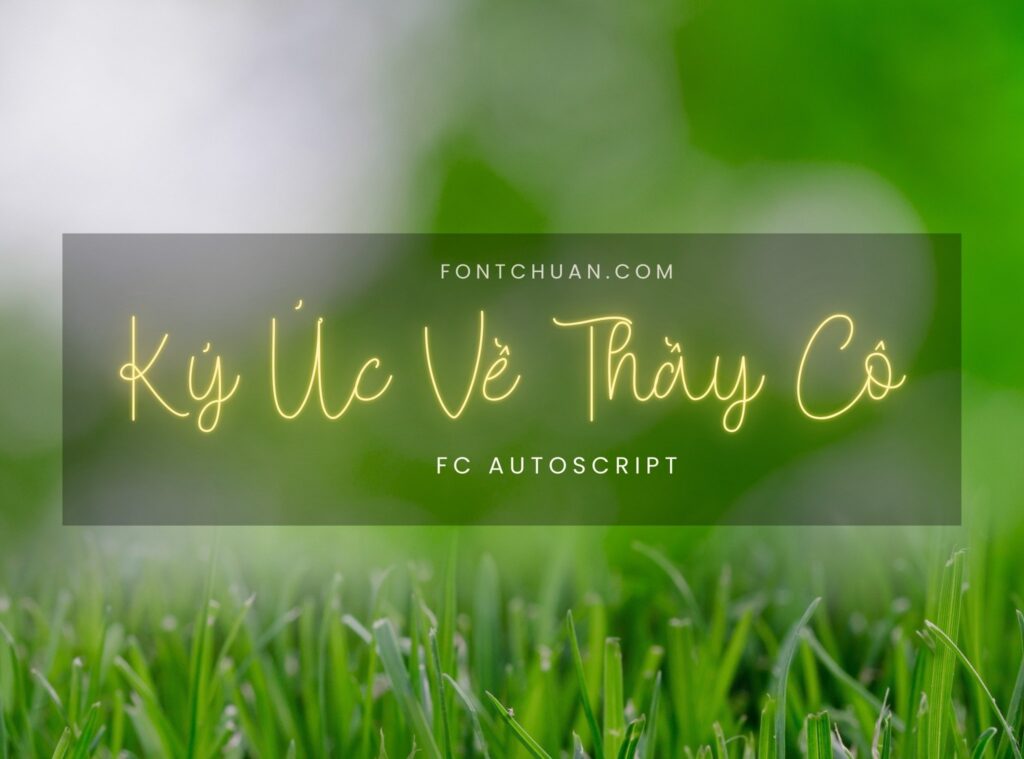
Font FC Autoscript Việt Hóa
Autoscript là một font chữ viết tay mảnh mai và tinh tế, được thiết kế bởi JD Studio và phát hành vào khoảng giữa năm 2024. Với các nét chữ thanh thoát và phong cách đơn giản, Autoscript mang lại cảm giác nhẹ nhàng và hiện đại, phù hợp cho các dự án thiết kế như thiệp mời, logo, tiêu đề và các ấn phẩm quảng cáo khác.
Thành viên của Font Chuẩn đã chọn lọc và sưu tầm Autoscript, đáp ứng nhu cầu đa dạng của bạn đọc và hỗ trợ ứng dụng thực tế trong các dự án thiết kế. Với cấu trúc chữ mềm mại, độ dày đồng nhất và thiết kế tinh tế, Autoscript phù hợp cho các thiết kế yêu cầu sự thanh lịch và chuyên nghiệp. Đặc biệt, font này thích hợp cho các ngành nghề như quảng cáo, thiết kế thiệp cưới và lĩnh vực thời trang, nơi cần sự kết hợp giữa thẩm mỹ cao và chức năng truyền tải thông điệp.